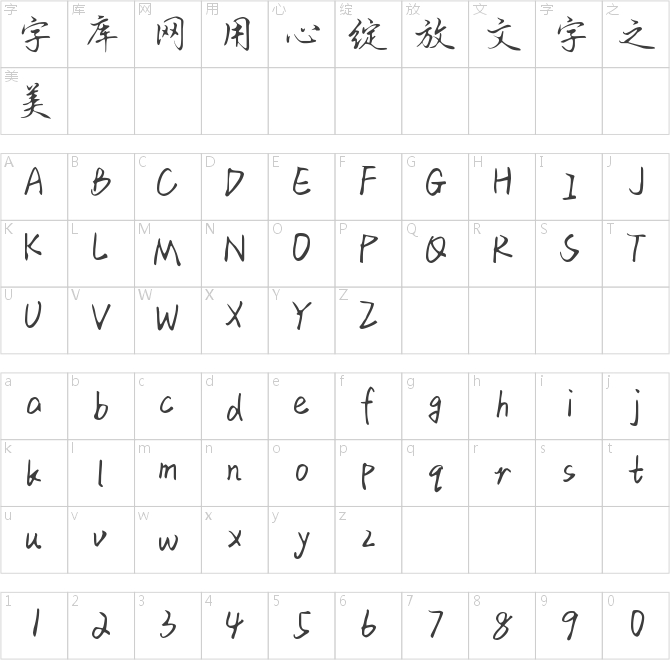
Aa星河攬?jiān)職w
Aa星河攬?jiān)職w字體字庫(kù)是一款讓人賞心悅目、百看不厭的中文字體,適合各類(lèi)廣告和產(chǎn)品包裝設(shè)計(jì)應(yīng)用,字體大小3.37MB,格式為ttf字體,上傳用戶(hù)是Aa字庫(kù),作者/版權(quán)方為Aa字庫(kù)